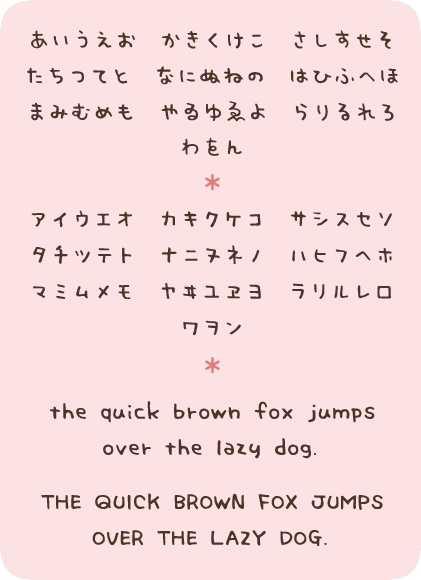
フォント「ころたんPro」
フォント「ころたんPro」は、ほのぼのころっとした手書き文字のフォントです。 【収録文字】 ●ひらがな●全角・半角カタカナ●全角・半角数字●全角・半角アルファベット●ギリシャ文字●ロシア文字●各種記号●JIS第一水準漢字●JIS第二水準漢字●IBM追加漢字 「ころたん」にはJIS第二水準漢字まで収録されていますが、漢字・多くの記号等は拙作の「こうさぎフォント」で補われています。 「ころたん」オリジナルの部分は、【ひらがな、カタカナ、アルファベット、数字、一部記号】のみであることをご了承ください。 禁止事項や詳しい使用規約などは、サイトの方をご確認ください。 http://cotorifont.net/ 「ころたんPro」は武蔵システム(http://opentype.jp/)のTTEditを使って作成しました。 また、glyphsapp.comさんのGlyphsを使って編集/出力しました。